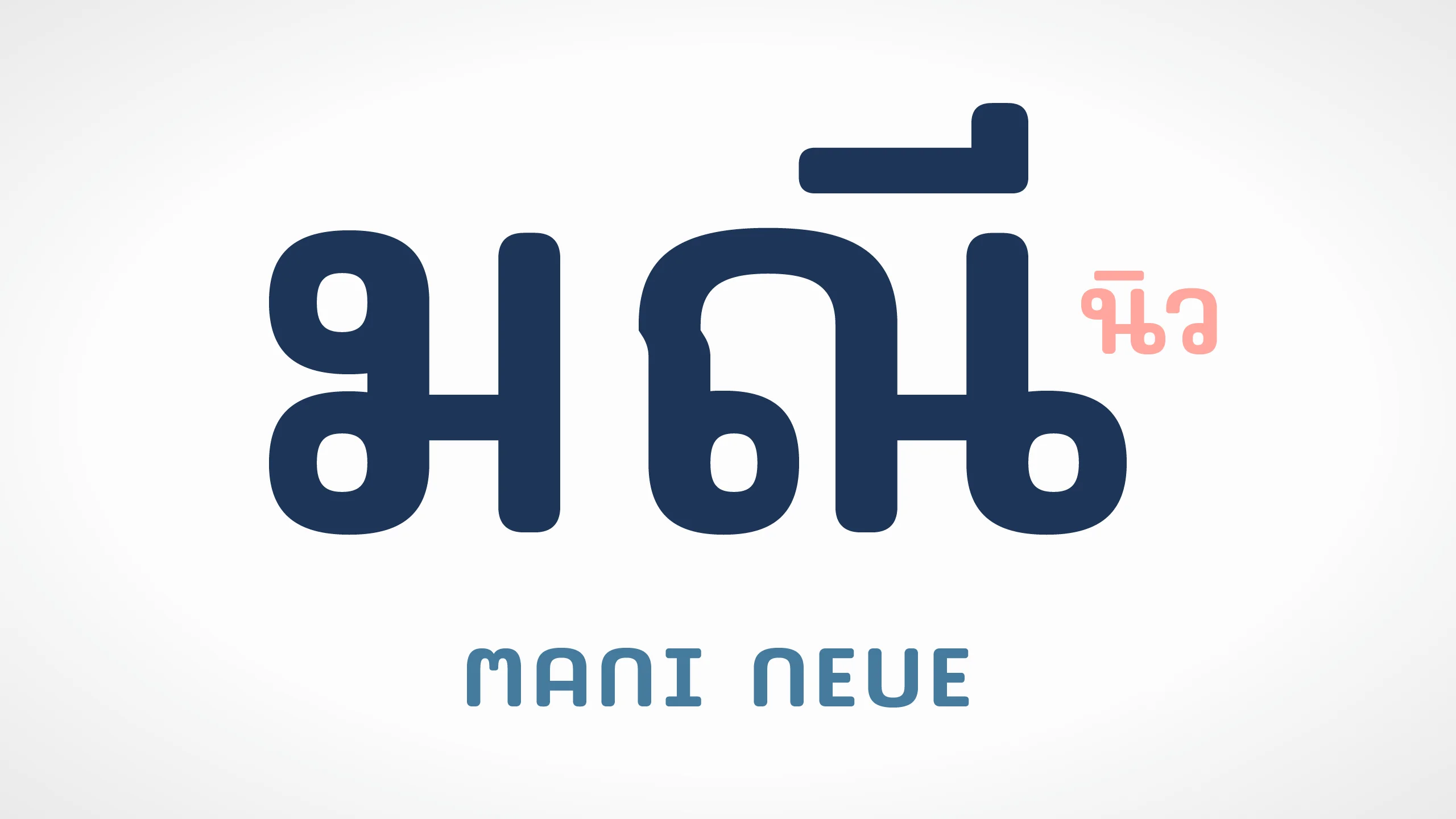
MANI NEUE
"มณี นิว | MANI NEUE" คือผลผลิตจาก REMAKE PROJECT ที่นำชุดอักษรยอดนิยมอย่าง "มณี-เมขลา" มาตีความและพัฒนาขึ้นใหม่ทั้งหมดเพื่อก้าวสู่มาตรฐานการใช้งานยุคปัจจุบัน โดยเรายังคงรักษาหัวใจสำคัญของต้นฉบับไว้อย่างครบถ้วน ทั้งความน่ารักที่เป็นธรรมชาติ การจัดวางที่ดูเป็นกันเอง และความเรียบง่ายที่ทำให้ใครเห็นก็รู้สึกสบายตา แต่ในเวอร์ชั่นนี้ถูกนำมาปรับปรุงลายเส้นให้มีความนุ่มนวลและสม่ำเสมอมากขึ้น เพื่อมอบบรรยากาศที่อบอุ่นและมีชีวิตชีวาให้กับทุกชิ้นงานของคุณ นอกเหนือจากรูปลักษณ์ที่ดูสดใส เรายังได้ทำการอัปเกรดขีดความสามารถแบบก้าวกระโดดเพื่อให้ "มณี นิว" เป็นฟอนต์ที่ทำงานได้อย่างไร้รอยต่อในระดับมืออาชีพ ด้วยการเพิ่มประสิทธิภาพด้านเทคนิคและจังหวะการจัดวางที่แม่นยำยิ่งขึ้น เหมาะอย่างยิ่งสำหรับงานออกแบบที่ต้องการความใกล้ชิดกับผู้คน ไม่ว่าจะเป็นการทำคอนเทนต์โซเชียลมีเดีย งานสื่อสิ่งพิมพ์แนวไลฟ์สไตล์ หรือการสร้างแบรนด์ที่ต้องการส่งต่อความรู้สึกที่เป็นมิตรและจริงใจ "มณี นิว | MANI NEUE" พร้อมจะเป็นเพื่อนคู่ใจคนใหม่ที่จะช่วยให้งานดีไซน์ของคุณดูดีมีสไตล์และเข้าถึงง่ายกว่าที่เคย